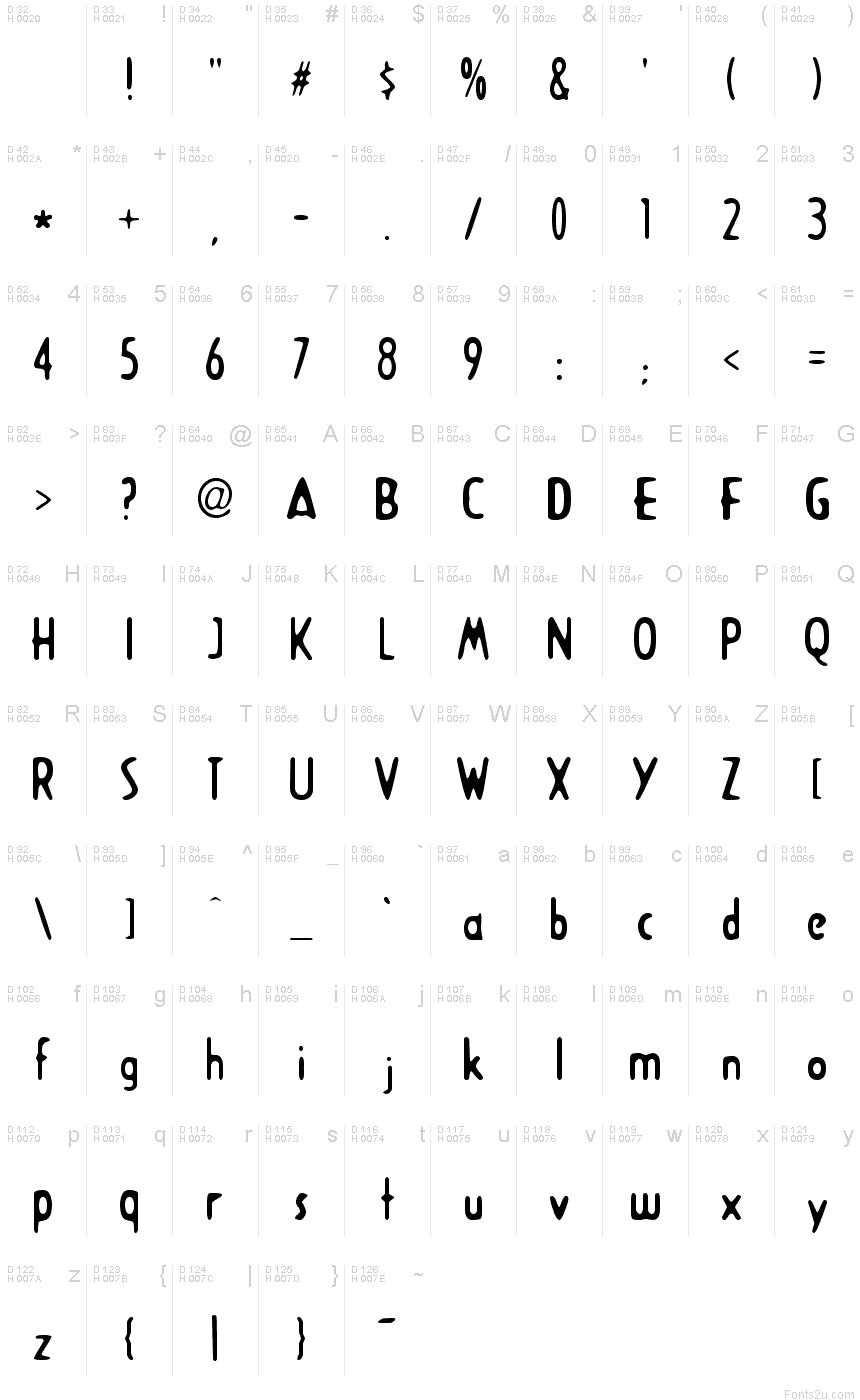
Liquid Nite 字体
Liquid Nite
Liquid Nite Productions
Andrew Hungerford
由 Zogoz 设计的 Liquid Nite 是一款免费的展示字体,具有粗厚、圆润的造型和略带侵蚀感的边缘,使字体看起来既柔和又带有一种斑驳的磨损感。小写字母紧凑且富有有机感,简单的点画和曲线赋予了这款字体手绘而非机械般的质感。
Liquid Nite 非常适合用于海报标题、音乐封面、游戏菜单、Logo 设计以及活动传单,因为其厚重的笔画在保持出色的可读性的同时,依然带有粗犷的风格化边缘。这款免费字体也适用于包装标签和社交媒体短文案配图,当您需要一种既随性又有质感,且不失清晰度的展示字体时,它将是理想的选择。